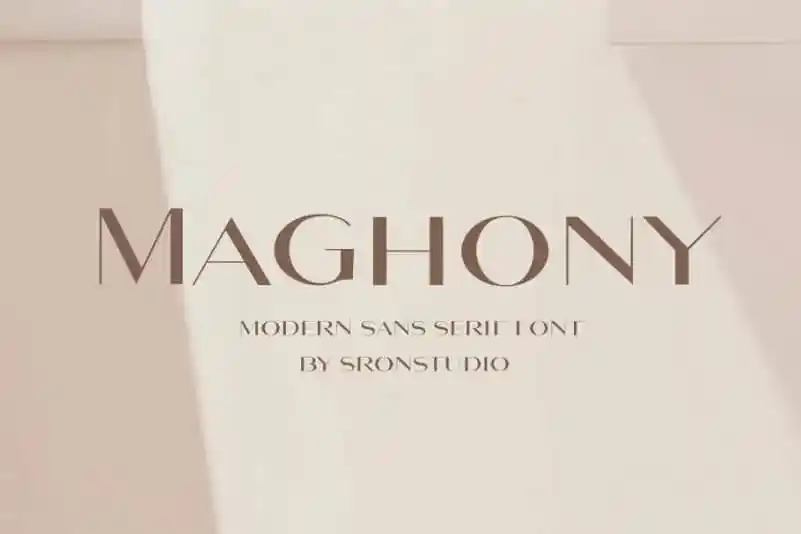
Maghony Sans Serif Font – Download Grátis
Maghony Sans Serif é uma fonte seríssima que exala sofisticação e autenticidade. Fabricada pela Sronstudio, essa elegante sans serif está pronta para servir como um elemento distintivo em diversas aplicações gráficas. Perfeita para estilos de marca, convites, papéis de parede, designs nupciais, posts nas redes sociais, anúncios, embalagens dos produtos, desenhos dos produtos, etiquetas, fotografia e até mesmo watermark ou eventos especiais, Maghony Sans Serif está sempre em sintonia com as tendências atuais. Composta pelo design de um único tipo, esta fonte oferece um toque sofisticado que torna o trabalho gráfico mais especial e atraente para qualquer projeto. O design minimalista, mas extremamente elegante desta fonte se encaixa perfeitamente em uma variedade de formatos e estilos. Seja você designer de moda ou blogueiro de fotografia, Maghony Sans Serif é o amigo ideal que adiciona um toque singular ao seu trabalho.